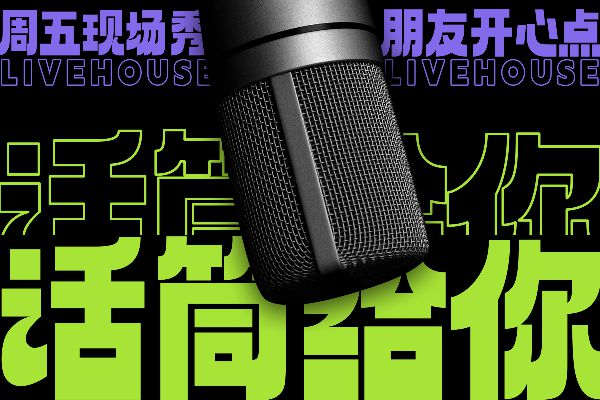
免费商用的创意字体下载去哪个网站?
你是否也遇到过这种情况:为了一个海报视觉,好不容易在网上找了一款极具张力的创意字体,成稿后才被提醒“这款字体未授权,商用可能面临几万元的赔偿”?这种在版权边缘试探的焦虑,是每个创意人共同的痛点。
如何能在不支付高昂授权费的前提下,合法合规地使用那些有设计感、有“灵魂”的创意字体?今天,我将基于自己长期的使用经验,为你深度复盘一个我几乎每天都在使用的神器——字由,并为你拆解如何高效寻找并利用那些免费商用的创意资源。
一、 为什么我会使用字由
丰富的创意字体
二、 字由中 4 款免费商用创意字体推荐
Aa厚底黑的设计非常大胆,将文字的底部笔画加粗,重心下沉。这种“下盘极稳”的设计,给人一种扎实、复古且带有一丝笨拙可爱的视觉冲击力。我常把它用在餐饮品牌的海报、复古风的电商促销页面,或者是需要强调“重量感”的主题标题上。
演示佛系体
演示佛系体线条纤细、随性,带有明显的手写感,笔画转折处非常圆润,没有任何侵略性。
在做生活方式类的设计时,佛系体能营造出一种“慢生活”的氛围。它不是那种能一眼抓人的字体,但它很耐看,能让观众的心瞬间安静下来。
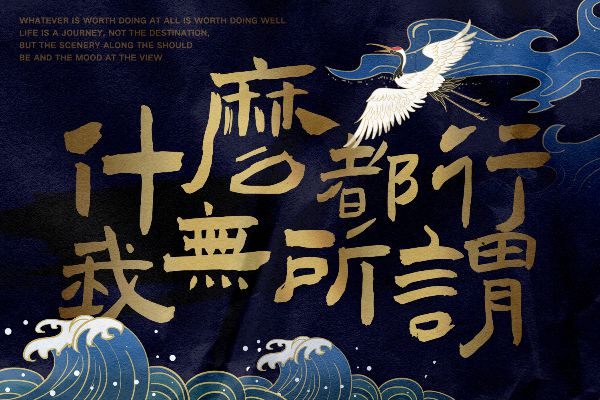
字由芳华体
芳华体是字由出品的一款非常有格调的字体。它的字形修长,线条纤细而挺拔,带有浓郁的民国美学色彩。
我曾在为一个旗袍品牌做宣传手册时全篇使用了这款字体。它那种若有若无的精致感,能瞬间拉高设计的档次。虽然它是免费商用,但其表现出的“贵气”完全不输给昂贵的付费字体。
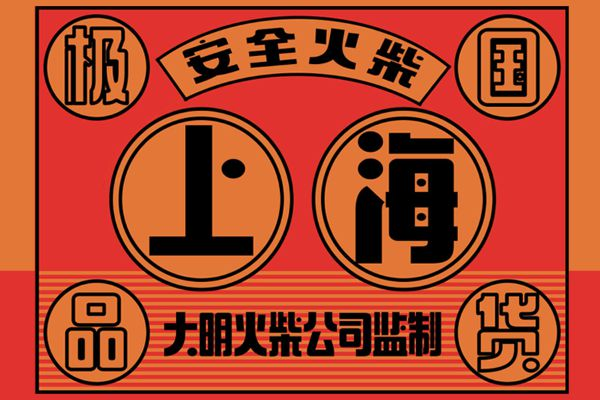
站酷文艺体
站酷文艺体笔画舒展,结构适中,既保留了印刷体的规范,又多了一份人文情怀。广泛应用于图书排版、长文标题、以及各类文创产品的包装。
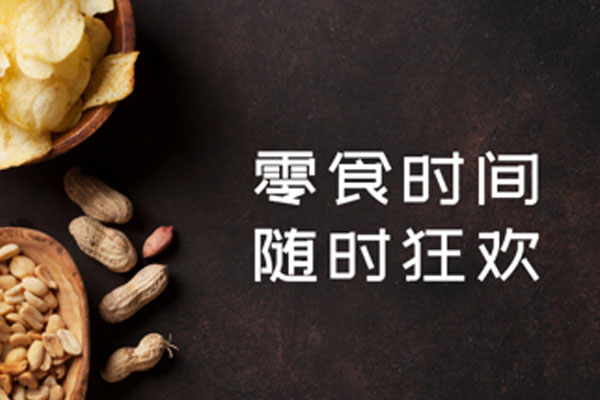
三、 除了字由,还有哪些创意字体免费下载平台?
100font
100font是一个极其纯粹的导航类网站。创始人非常执着,几乎收集了全网所有发布过的免费商用中文、日文及英文美术字体。
它的优点是“全”,且每一款字体都附带了原始的授权链接或官方说明页面。如果你在寻找某款特定的小众免费字体,在 100font 上基本都能搜到。它的界面很简洁,没有多余的干扰信息,是设计师必备的收藏夹网站。
Google Fonts
国际公认的开源字体库。如果你需要找英文创意字体,这里是全球最权威的地方。